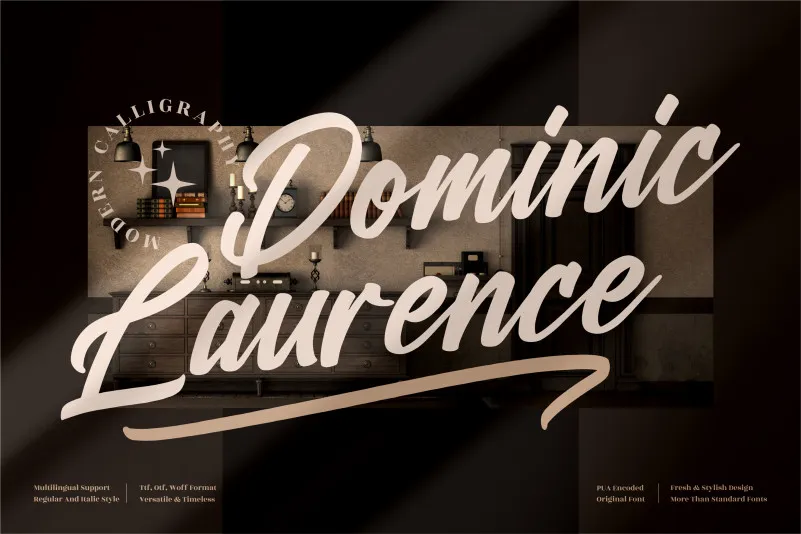
Esta é uma bela e equilibrada fonte script. Com suas curvas suaves, ela se destaca perfeitamente para aplicações em marcas fashion ou projetos editoriais. Esta fonte possui PUA (Unicode) encoding que significa você pode acessar facilmente todos os gráficos e swashes. Uma excelente opção para designers que procuram uma fonte elegante e sofisticada, essa é perfeita tanto para um estilo minimalista quanto para um design mais elaborado. Ideal para criar logos, embalagens de produto ou qualquer outro tipo de arte em editorial.